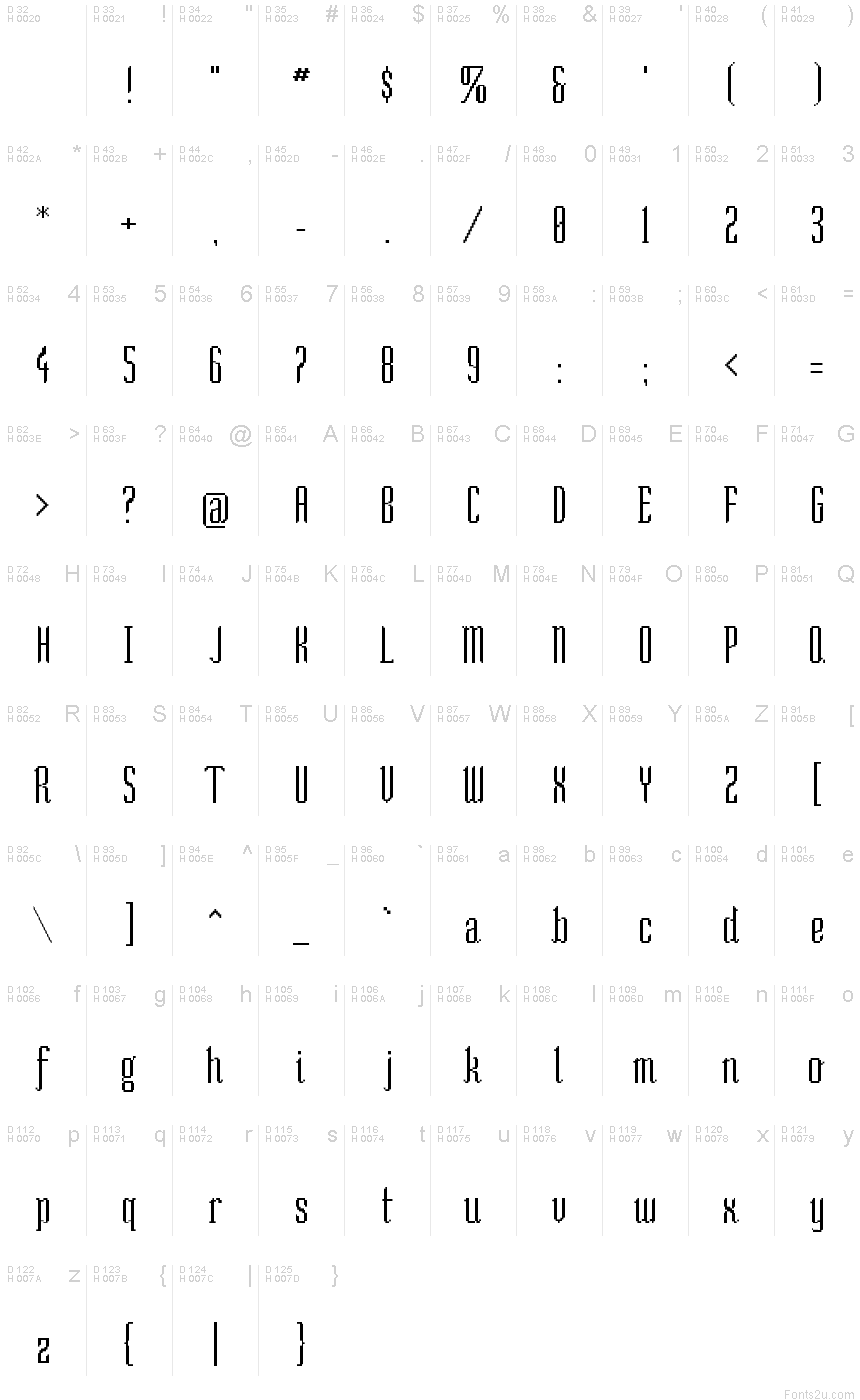
So Condensed من Apostrophic Labs هو خط بكسل سيريف مجاني يتميز بطابع عصري حاد يشبه خطوط Didone. تأتي حروفه بتصميم مرتفع وضيق، مع زوايا بكسل واضحة ووصلات دقيقة وزوائد خطية عريضة تمنح الخط بأكمله لمسة هشة ومميزة تذكرنا بعصر الملصقات القديمة.
هذا الخط مثالي لرسومات الواجهات ذات الطابع القديم (ريترو)، وعناوين المجلات، وبطاقات العناوين، وتصميمات الأغلفة، والشعارات المدمجة التي تحتاج إلى لمسة من الأناقة الكلاسيكية ضمن شبكة رقمية. وباعتباره خطاً مجانياً، فهو يعمل بشكل ممتاز في العناوين القصيرة واسكتشات الشعارات، حيث يضفي إيقاعه المكثف ولمسة البكسل الواضحة طابعاً مدروساً ومناسباً لحقبة زمنية محددة، حتى مع استخدام عدد قليل من الحروف.